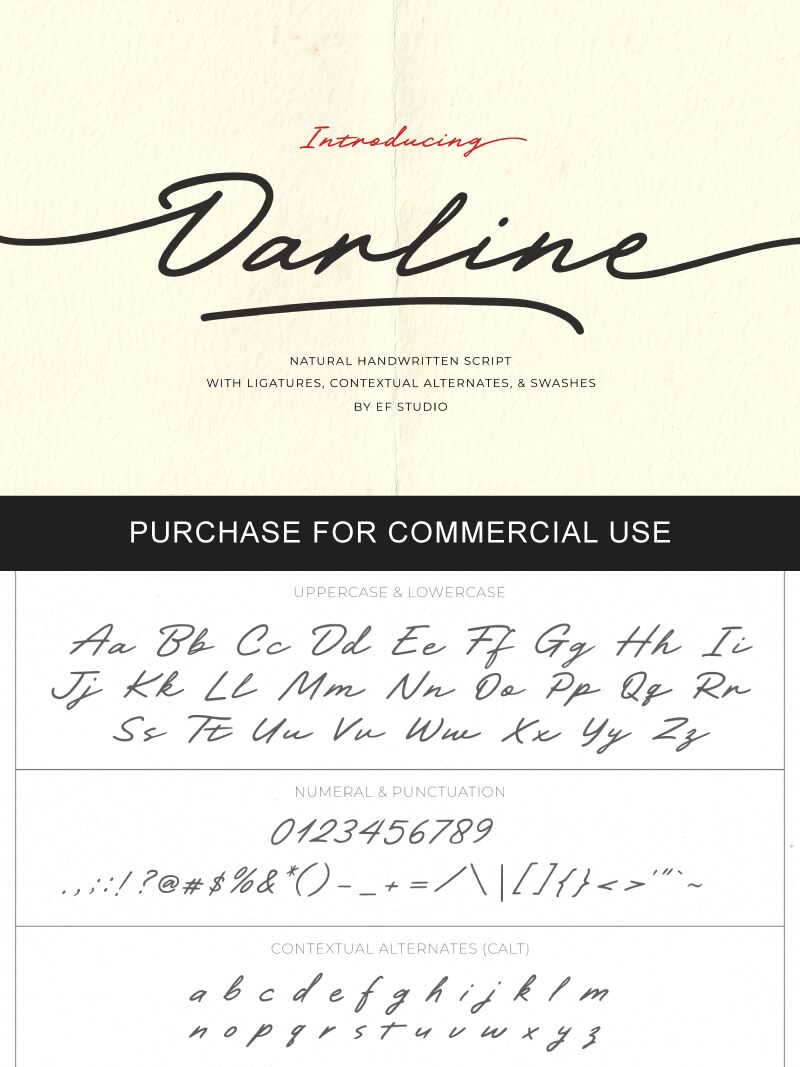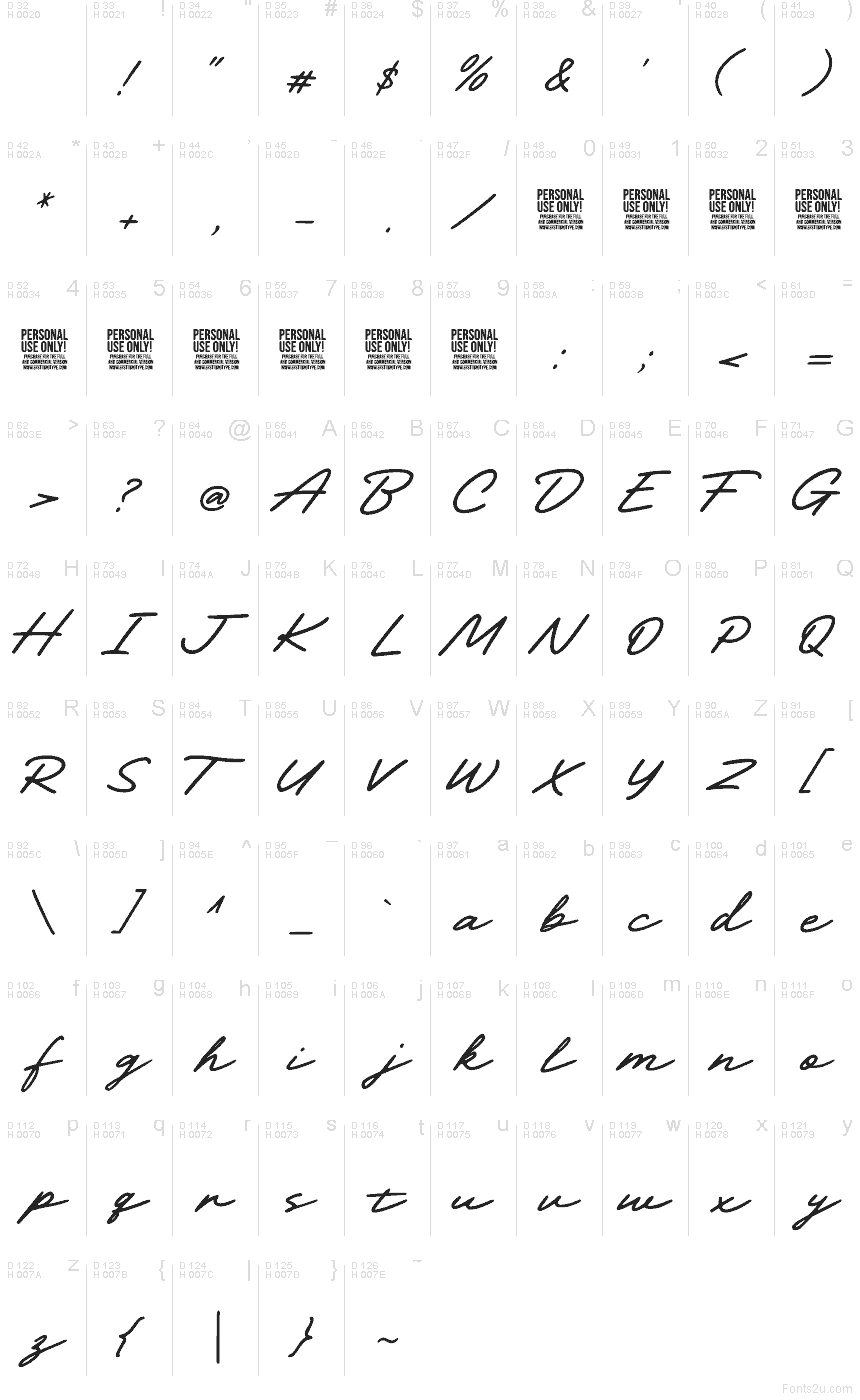
Darline di Ef Studio è un font calligrafico gratuito, caratterizzato da un ritmo fluido simile a una firma e da tratti lunghi e sinuosi. Le lettere si susseguono rapidamente, conferendo la leggerezza spontanea di una scrittura a mano libera, piuttosto che la rigidità di una calligrafia formale.
Questo rende Darline una scelta naturale per loghi di boutique, packaging, citazioni sui social media, titoli di inviti e branding nel settore beauty. I suoi tratti estesi in entrata e in uscita regalano alle frasi brevi un tocco di eleganza, perfetto per ancorare un logotipo, incorniciare l'etichetta di un prodotto o aggiungere un tocco personale a biglietti e grafiche promozionali.